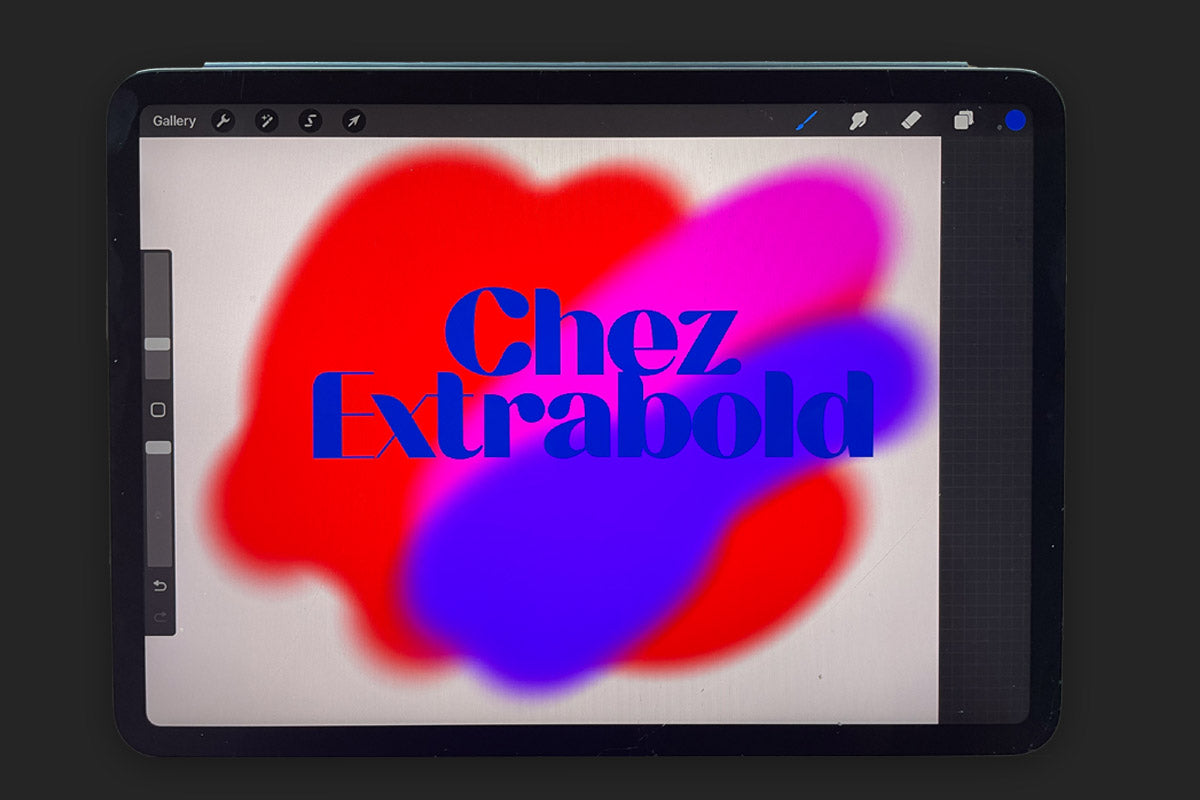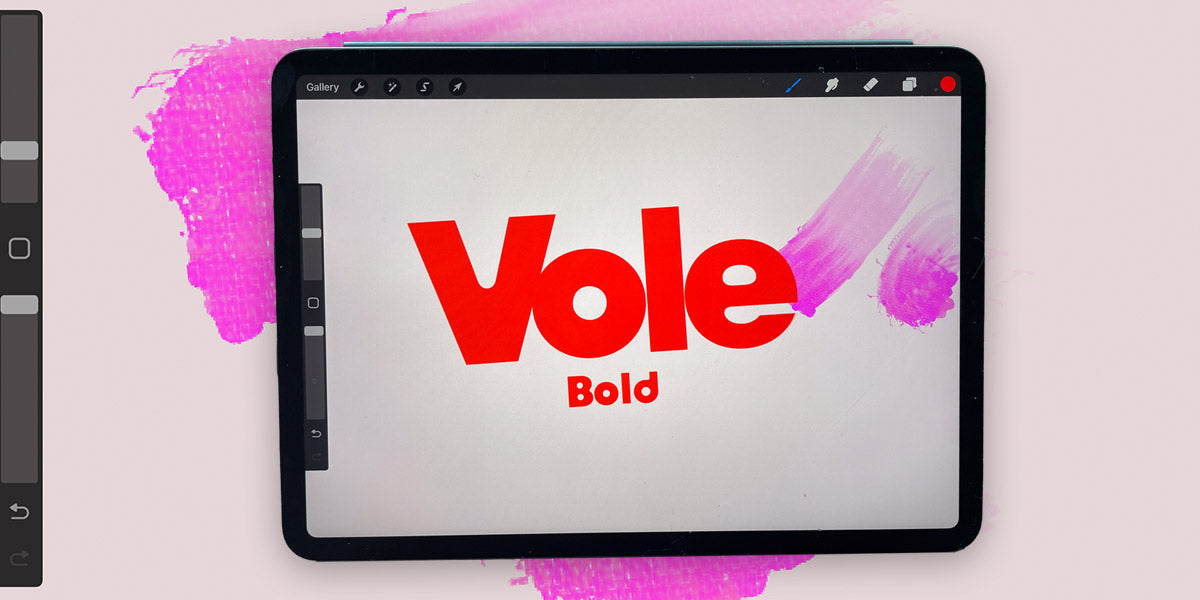
Schauen Sie sich diese sechs coolen Schriftarten für Procreate an – von Retro bis Kursiv und süß.
1. Vole Bold, Schriftart mit abgerundeten Punzen
Vole Bold ist eine geometrische Schriftart mit ausgefüllten Punzen und Tintenfallen für einen Vintage-Wassereffekt.
2. Chez ExtraBold, Bio-Typ
Chez ExtraBold ist ein süßer Bio-Typ mit einer warmen, persönlichen Ausstrahlung.
3. Lace Light, handgeschriebene monolineare Schriftart
4. Pout Black, cooler Reverse-Contrast-Typ
5. Goji ExtraBold, coole Blasenschriftart
6. Loco Bold, lustige Blasenschrift mit Highlights